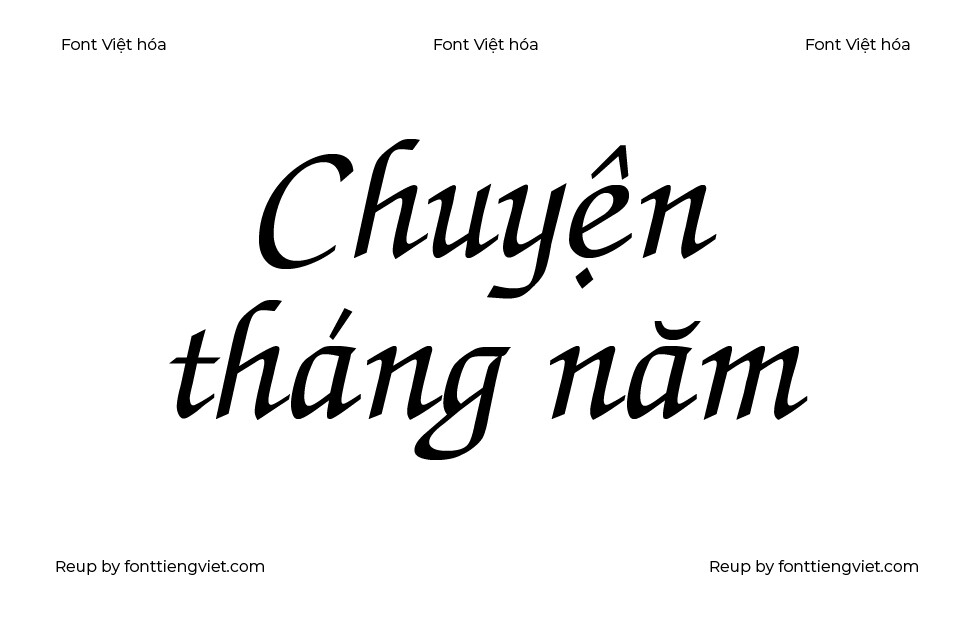
Font Việt hóa VNI Zap
Trong thế giới thiết kế đồ họa, việc lựa chọn phông chữ phù hợp đóng vai trò quyết định đến tính thẩm mỹ của sản phẩm. Font Việt hóa VNI Zap là một trong những bộ font kinh điển, được nhiều thế hệ người dùng Việt Nam yêu thích nhờ phong cách nghệ thuật độc đáo. Với những đường nét mềm mại và tinh tế, bộ Font Miễn Phí này không chỉ giúp nội dung trở nên nổi bật mà còn mang lại cảm giác chuyên nghiệp, sáng tạo cho mọi văn bản. Đối với các bạn học sinh và giáo viên, việc sử dụng bộ font này sẽ giúp các bài thuyết trình hay tài liệu học tập trở nên sinh động và thu hút hơn bao giờ hết.
Đặc điểm nổi bật của Font Việt hóa VNI Zap
Phong cách thiết kế và ứng dụng thực tế
Bộ Font Việt hóa VNI Zap sở hữu cấu trúc đường nét thanh mảnh nhưng vô cùng chắc chắn, tạo nên sự cân bằng hoàn hảo cho thị giác. Khác với các font chữ hệ thống thông thường, VNI Zap mang đậm dấu ấn của phong cách thư pháp hiện đại, rất phù hợp để làm tiêu đề báo tường, thiệp mời hoặc các biểu ngữ trang trí trong nhà trường. Nhờ được việt hóa kỹ lưỡng, người dùng có thể dễ dàng gõ các ký tự có dấu theo bảng mã VNI mà không lo gặp lỗi hiển thị, giúp quy trình thiết kế trở nên mượt mà và hiệu quả hơn.